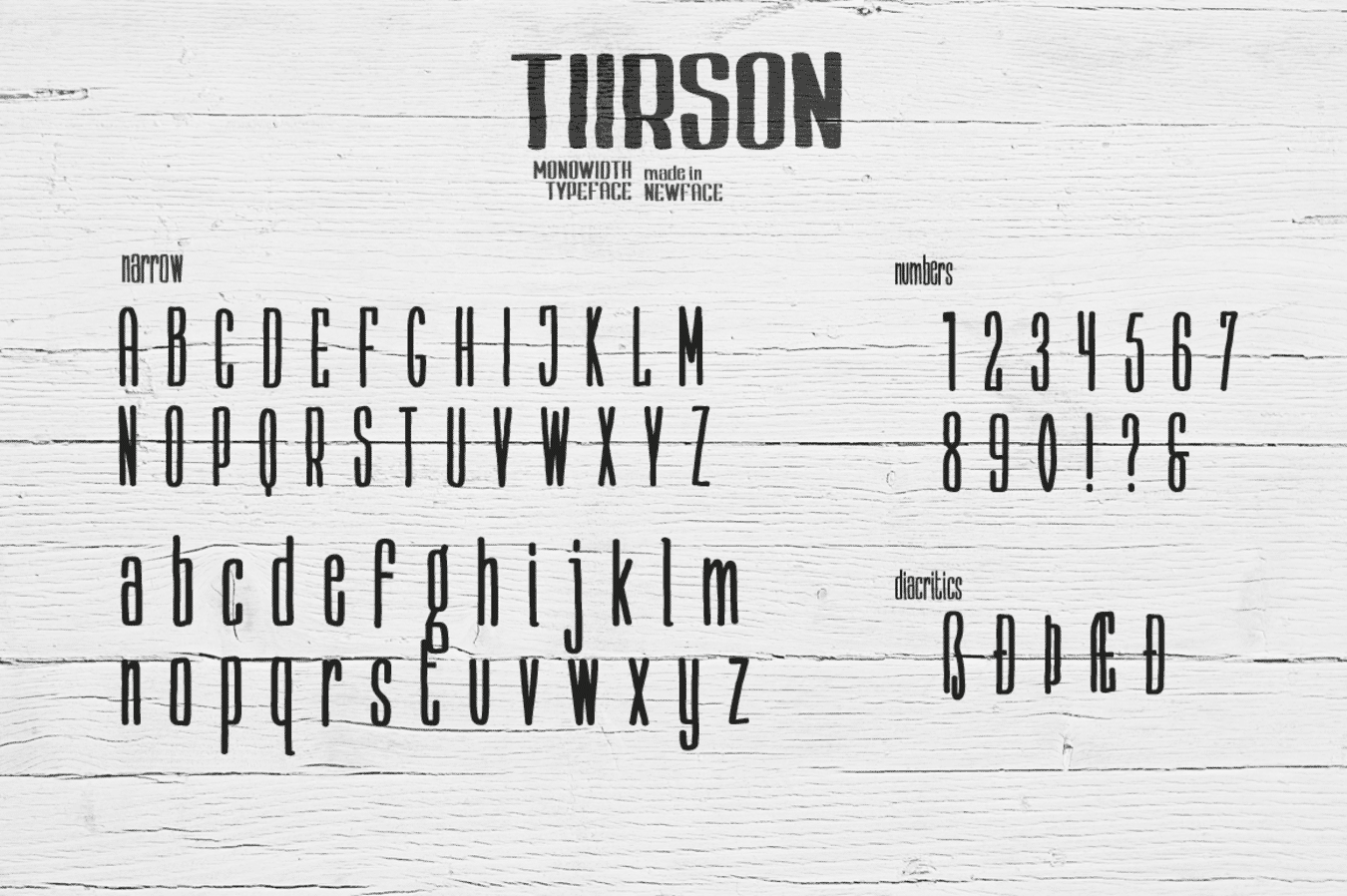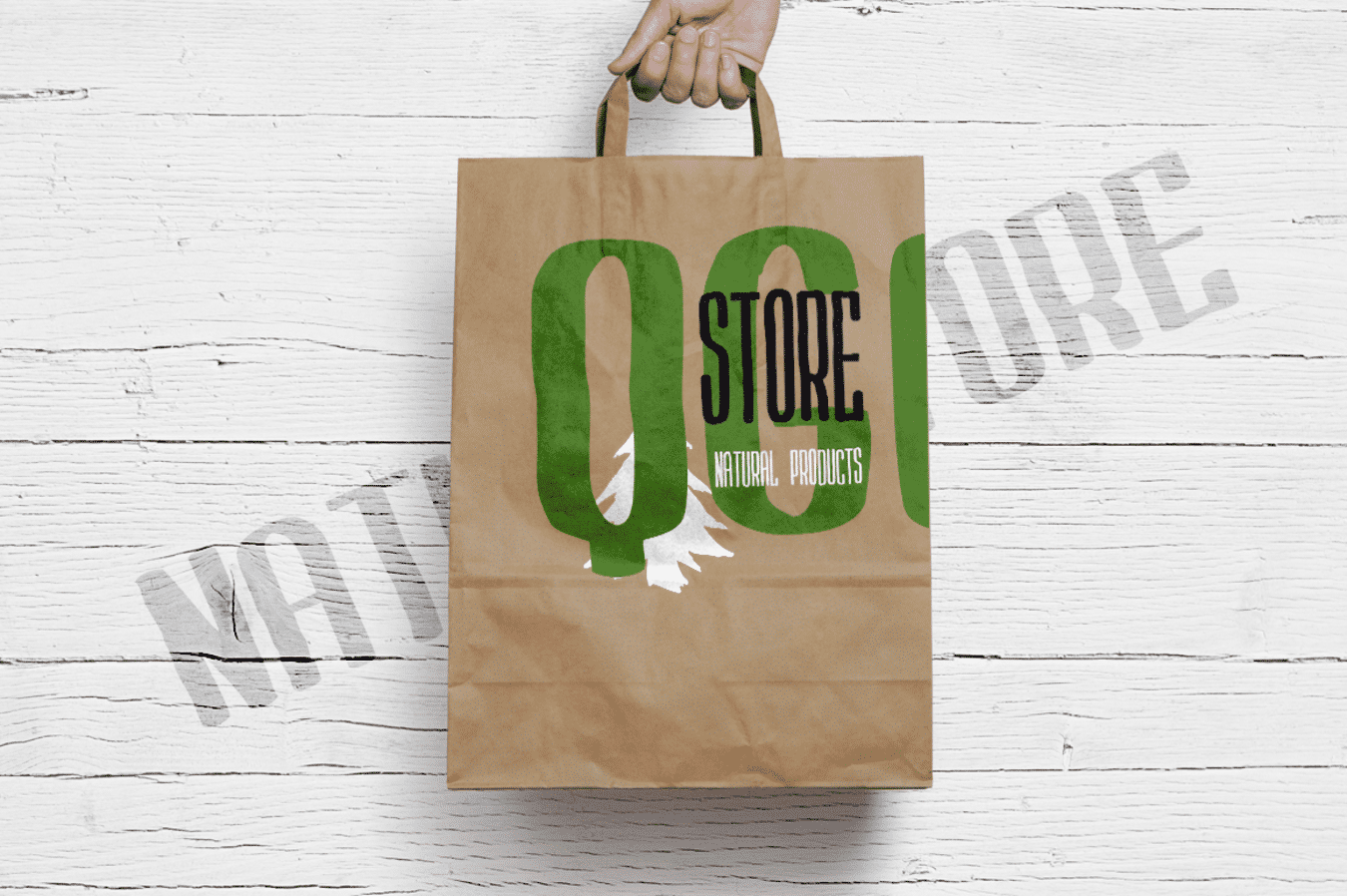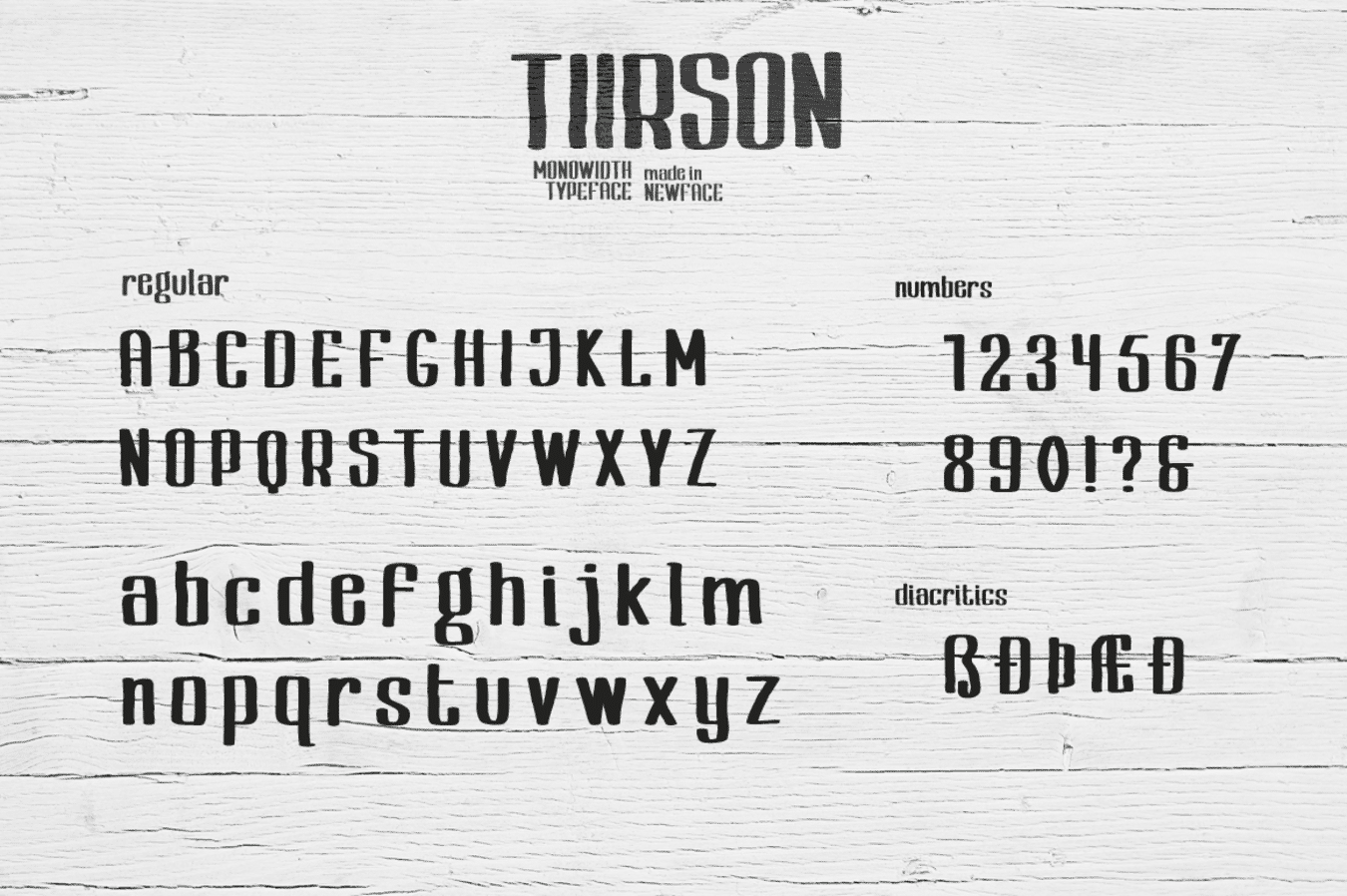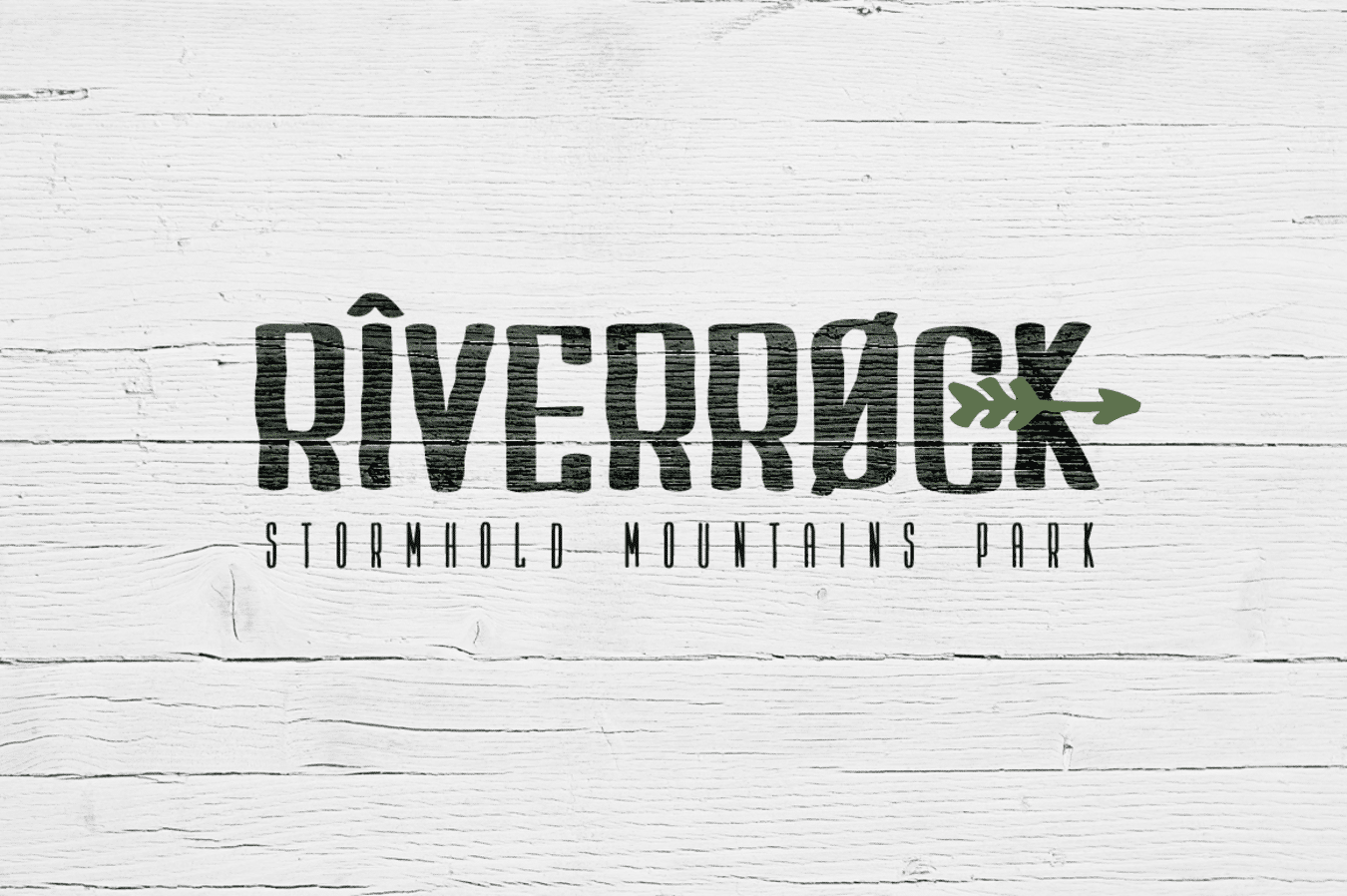
单声道宽正宗手写字体二人组,Tiirson Typeface Duo
Mono width authentic handwritten typeface duo, Tiirson Typeface Duo
介绍新的原始字体Tiirson!它是单声道宽度字体,适用于标题,品牌,服装设计等。 Tiirson是具有北方人物的真实手写字体。它包含标准的拉丁字母,数字,变音符号和支持欧洲 - 东欧语言。此字体包中包含常规和窄字体版本。 Tiirson附带OTF和TTF文件。